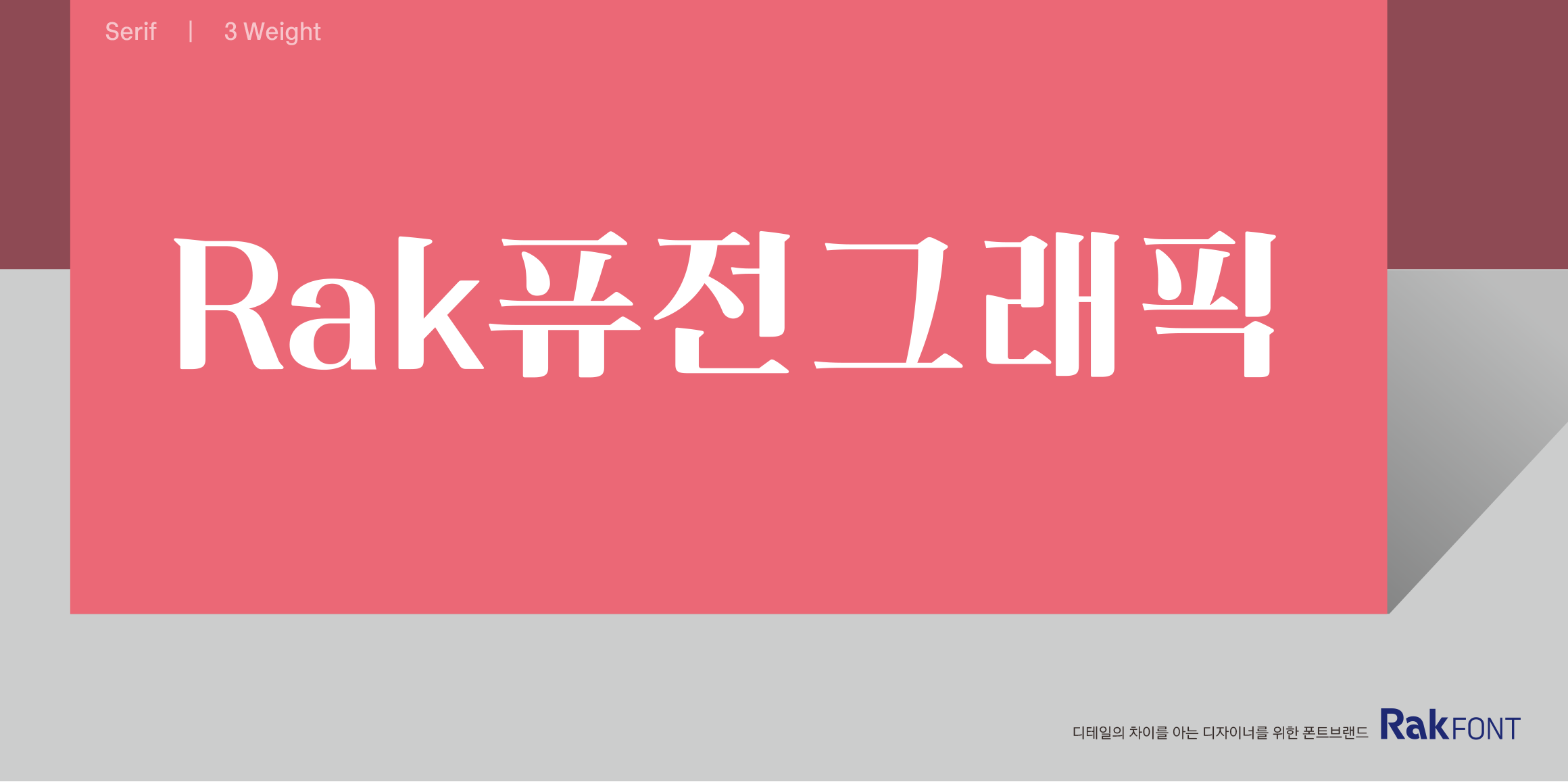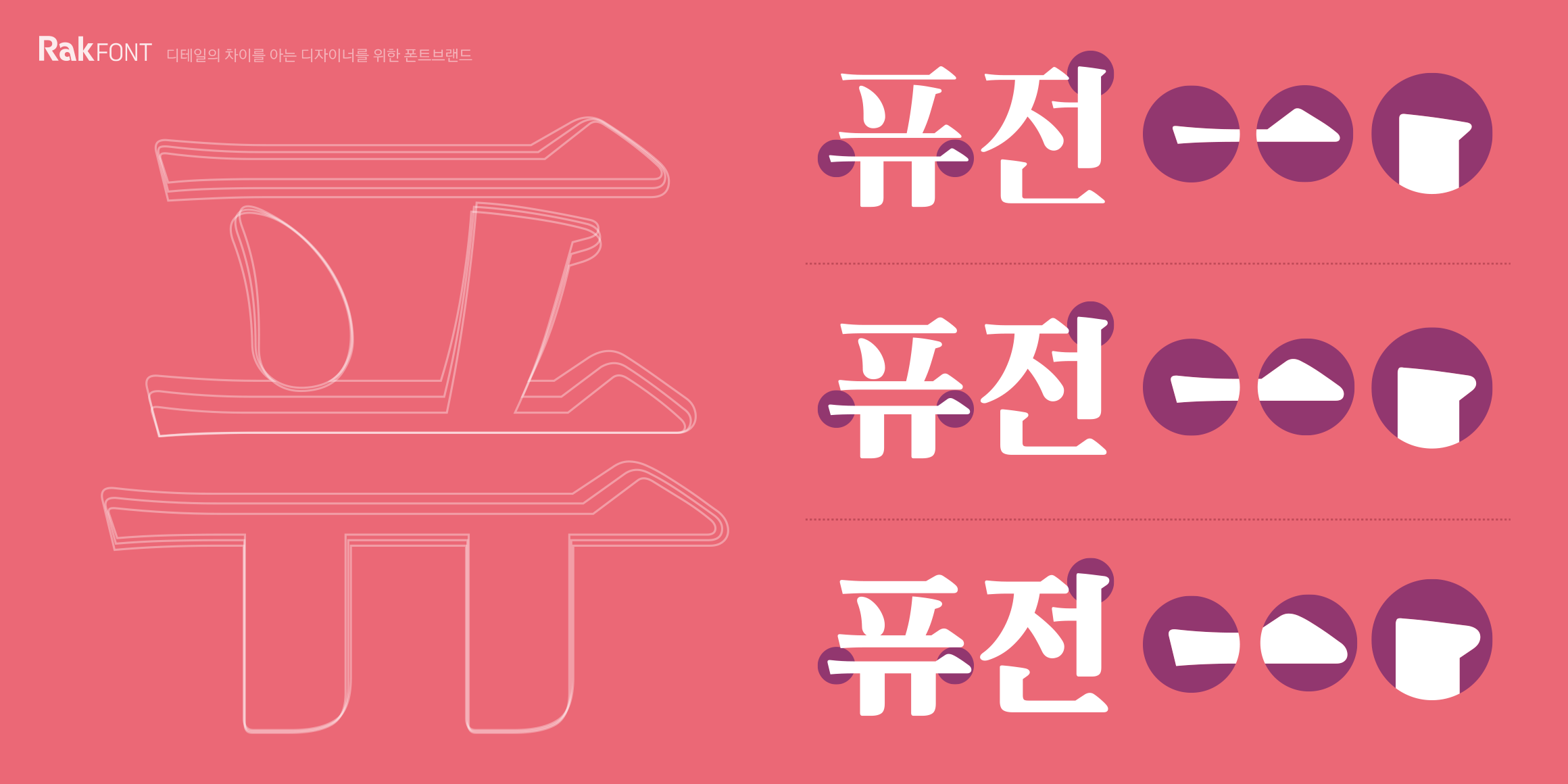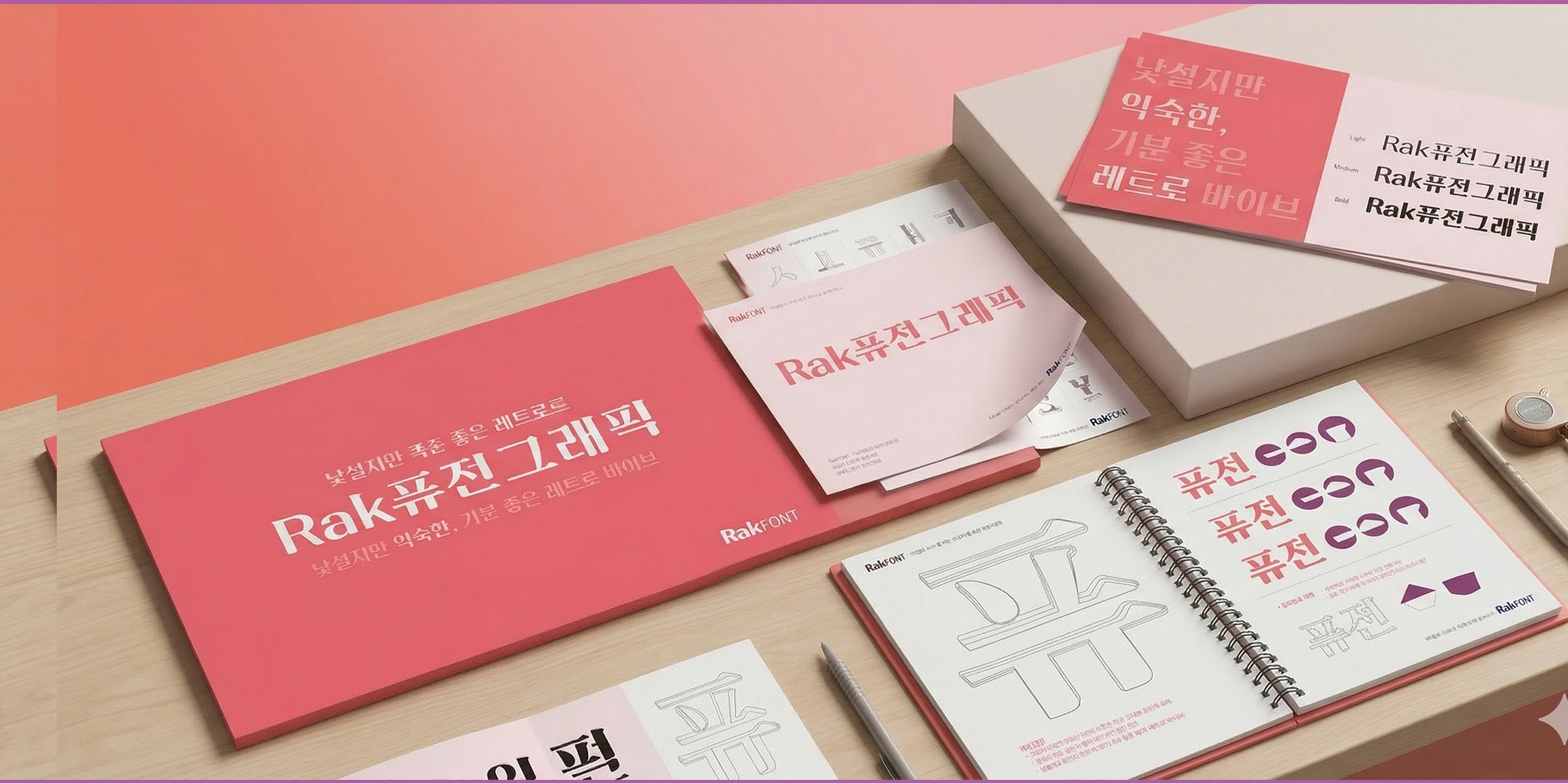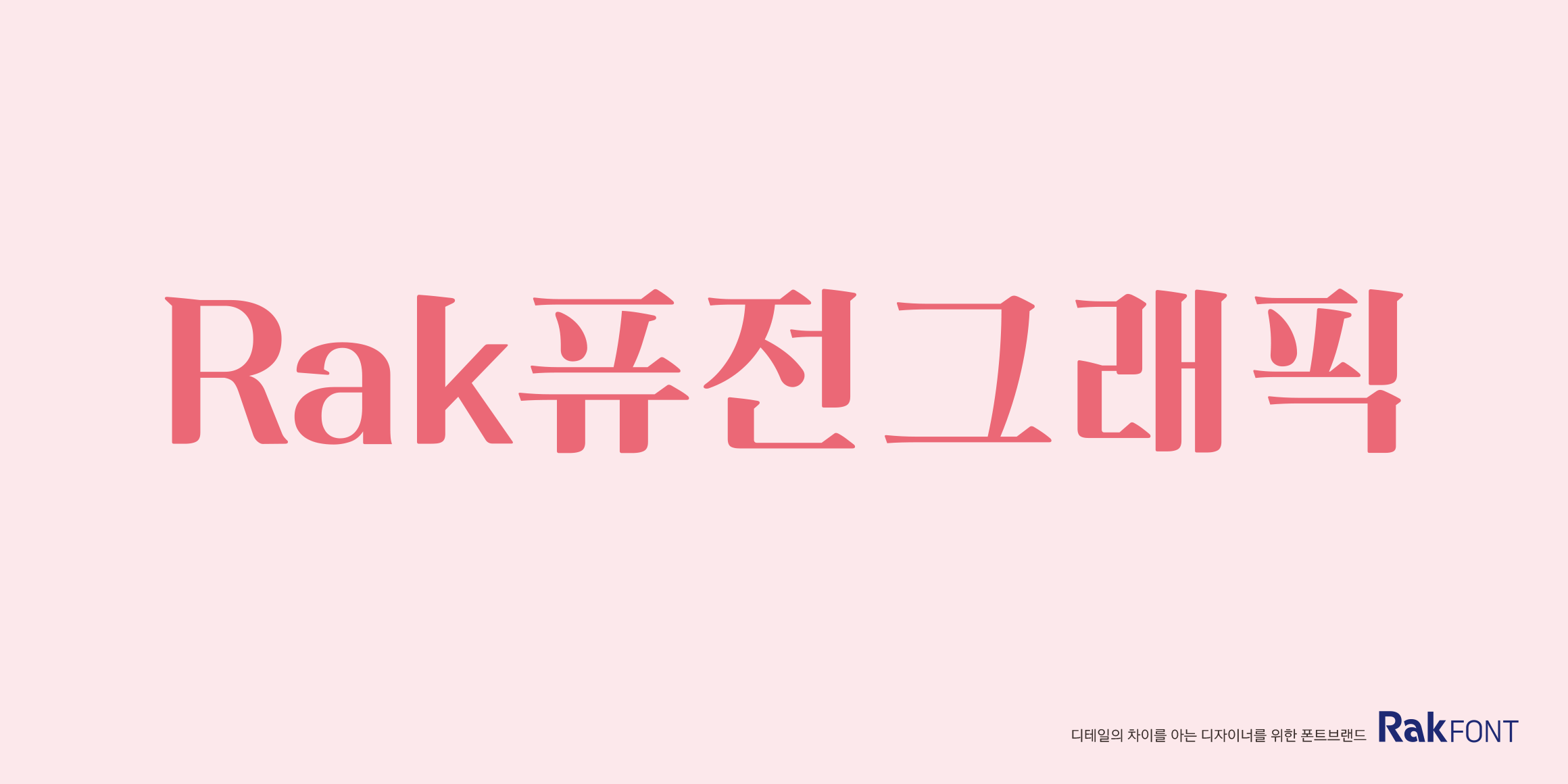
과거의 향수를 자아내는 레트로 무드에 시선을 사로잡는 역방향 세리프 디테일을 더해 유니크한 개성을 살렸습니다. 기존 그래픽 폰트들의 한계를 넘은 폭넓은 굵기 지원으로 디자인의 자유도까지 극대화했습니다. 독특한 시각적 재미와 실용성을 겸비한 감성 폰트를 찾고 있다면 'Rak퓨전그래픽'을 경험해 보세요.